タイププロジェクト、フィットフォントサービスの 欧文フォントにBlaze Type の6 ファミリーを追加
タイププロジェクト株式会社(東京都練馬区 代表取締役社長 鈴木 功、以下タイププロジェクト)は、本日、フィットフォントサービスに新しくBlaze Type(ブレイズタイプ)の欧文フォントを追加したことを発表いたしました。
Blaze Typeは、フランス リヨンに拠点を置く独立系タイプファウンダリーで、コンテンポラリーなリテールフォントとカスタムフォントの制作に力を入れています。その特徴は、リリースするフォントが多岐にわたることで、多くの言語に対応しさまざまな代替文字やスタイルとウエイトの幅広いフォントファミリーを展開していることです。
タイププロジェクトは、ウエイトやコントラスト、字幅、フトコロ軸を変更した場合でも、書体を常に理想的な設計に保つシステムを開発しました。フィットフォントサービスは、この機能を活用することで、ダイナミックに変化しながらもデザインの一貫性と品質を保持することを実現します。AXIS FontやTP明朝、TPスカイなどタイププロジェクトのそれぞれの書体で500から10,000以上のバリエーションを用意していますので、他社の欧文フォントに合わせて調節することで和文と欧文の適正なバランスを得ることができます。
タイププロジェクトでは、グローバル展開やブランディングを重視する企業に向けて、海外のパートナーと協業して和文と欧文が美しく調和したフォントを提供しています。今回、Blaze Typeが新たにフィットフォントパートナーに加わりました。
フィットフォントサービスに追加したBlaze Typeの欧文フォントは、「ヨハネの黙示録」からインスピレーションを得たApocを始め、Area、Inferi、Rules、Sigurd、Slussenの6ファミリーで、全51フォントです。
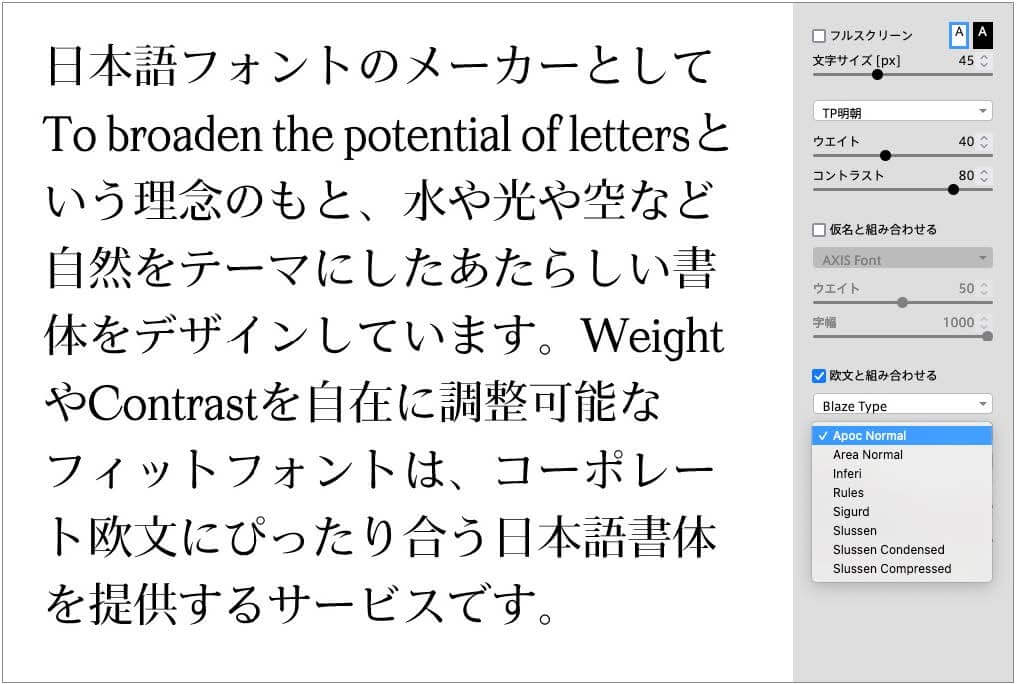
Blaze Typeの創立者でタイプデザイナーのMatthieu Salvaggio氏は、「以前からアジアの、とりわけ日本の会社と関わりたいと思っていました。TPスカイの核心を突いたデザインはエレガントで安定感があり、とても好きです。フィットフォントのようなサービスを提供するというのはすばらしい発想だと思います。このサービスに参加できることが本当に光栄で嬉しく思います」と述べています。
神話や建築からインスピレーションを得たフォント / Blaze Type
タイププロジェクトでは、企業のメッセージを伝えるための手段としてフォントによるブランディングを提案しています。フィットフォント技術を用いて、市販されていないウエイトや、欧文組替え、オリジナルのひらがなやカタカナを開発するなど、世界有数のグローバル企業にコーポレートフォントを提供しています。
- ・株式会社TBSホールディングス/株式会社TBSテレビ
社内資料や番組テロップなどのデザインを同じ見え方にするため、コーポレートフォントとして最適な数値をフィットフォントから選択し「TBSゴシック TP」と「TBS明朝 TP」を提供しました。また、欧文フォントを新規開発し、和文部にはAXISフィットフォントを組合せたブランディングフォント、「TBS Sans TP」も提供しています。 - ・サントリーコミュニケーションズ株式会社
サントリーコミュニケーションズには、狭いスペースに多くの情報を記載でき、かつ可読性を維持するという要望に応えた、表示組みのためのカスタマイズフォント「AXIS SUNTORY TP」を提供しました。 - ■ サービス詳細